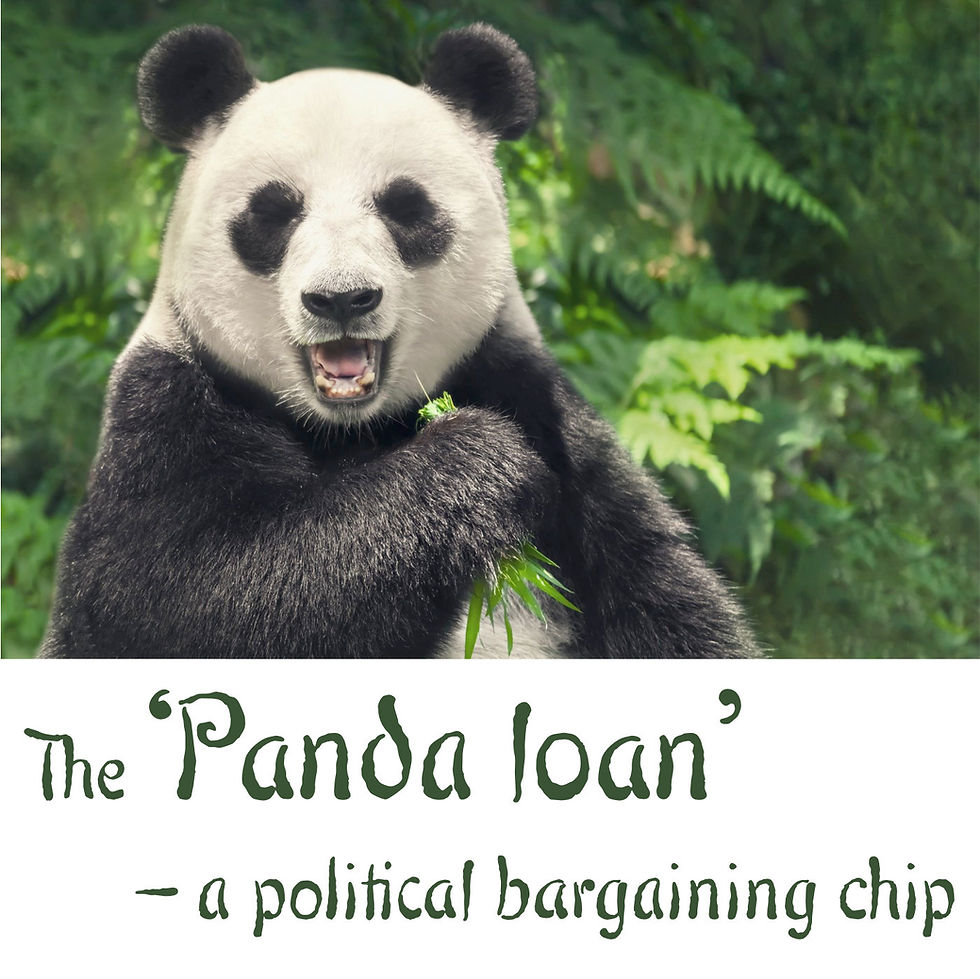
Eine reizvolle Schmuckschrift aus einem Schriftmusterheftchen von ca. 1900, erschienen im Otto Maier Verlag, Ravensburg.
Das Heft trägt den Titel: „Schriften-Sammlung für Techniker. Verkleinerte Schriften der wichtigsten Alphabete“, herausgegeben von Karl O. Maier.
Formen und Duktus der Façade Pro sind sichtlich vom Jugendstil beeinflusst.
In der Originalvorlage von Karl O. Maier erscheint nur das lateinische Alphabet. Alle anderen Zeichen, insbesondere die griechischen und kyrillischen Buchstaben wurden aus Bestandteilen der Vorlage nachempfunden.
Den echten „handgemachten“ Charakter erhält so eine Schrift dadurch, dass gleiche Buchstabenformen sich nicht ständig wiederholen – wie es bei der Handschrift ja auch ganz normal ist.
Dank OpenType-Technologie erscheinen einzelne Schlüsselbuchstaben der Façade Pro je nach Kombination in verschiedenen Alternativformen. Es ist zum Beispiel ein sichtbarer Unterschied, ob nach dem e ein i oder ein l folgt. Nach diesem Prinzip sind in der Façade Pro zahlreiche Buchstabenkombinationen durch alternative Zeichenformen definiert, so dass ein lebendiger Gesamteindruck entsteht.